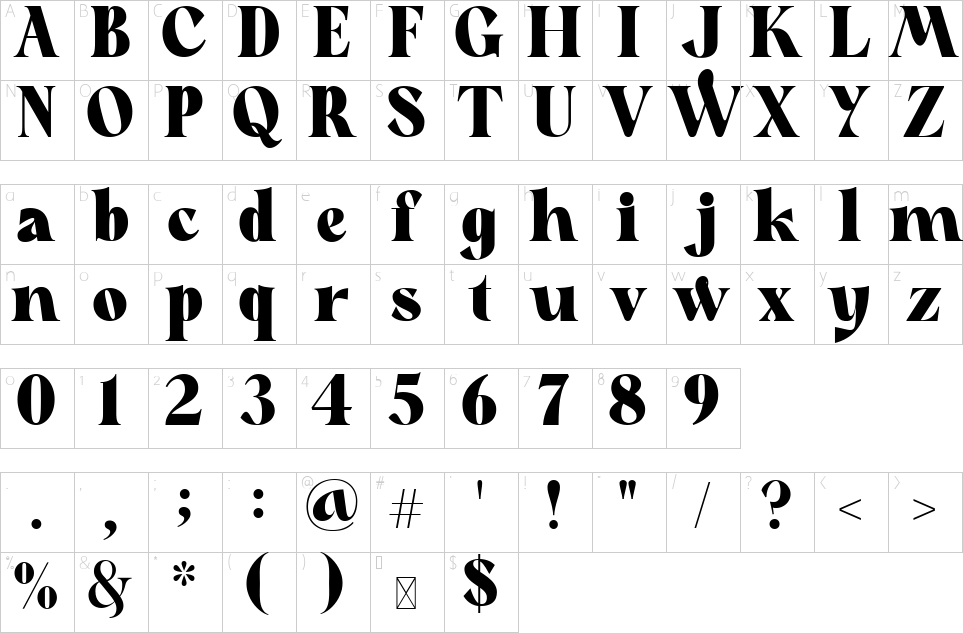
A fonte “Potential” é uma opção de grão-mestre gráfica e fácil de usar, perfeita para projetos em qualquer plataforma, seja Windows ou Mac. Ela foi projetada pelo 177Studio.com e disponibilizada gratuitamente em 2023. Com uma interface limpa e elegante, a fonte é adequada para textos de página inicial, designs de marca e aplicações de escritório. Não há dúvida de que “Potential” será uma escolha sólida para qualquer designer que busca uma opção de fonte fresca e de alta qualidade para suas próximas criações. A fonte é baixada com frequência, evidenciando sua popularidade e relevância no mercado. Com a “Potential”, você traz mais vida e estilo às suas criações.